創業100年を迎えたフォントメーカー「イワタ」をご存知ですか? イワタが開発したUDフォントや新聞書体は誰もが必ず⽬にしたことがある書体です。
フォントメーカー「イワタ」のルーツを探る
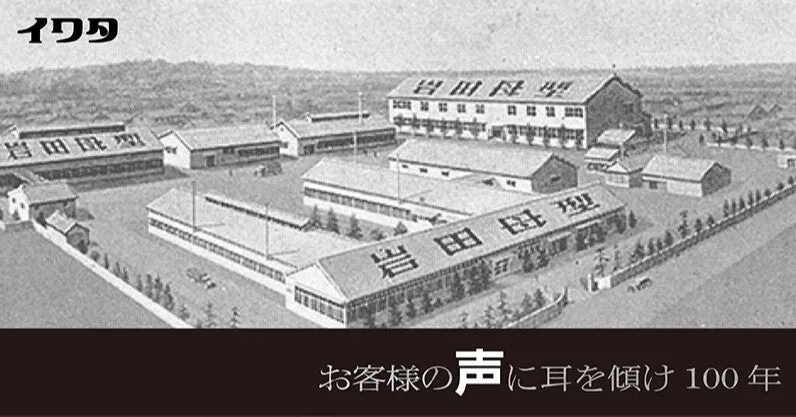
皆さんは、イワタというフォントメーカー、ご存じでしょうか? 1920年(⼤正9年)に岩⽥百蔵⽒が京橋に設⽴した「岩⽥活版⺟型製造所」がイワタのルーツです。ということで、イワタは昨年2020年で100周年を迎えました。おめでとうございます。
イワタの⼯場は、1923年(⼤正12年)の関東⼤震災のあと、⼤森に移転しました。1950年代の当時、⽇本に数台しかなかったベントン彫刻機を導⼊し、鋳造活字の元となる⺟型の⾼精度化と⼤量⽣産を実現し、⽇本最⼤の⺟型製造⼯場に成⻑しました。
1950年代は活版印刷が主流の時代でした。活字地⾦(鉛、錫、アンチモンの合⾦)を鋳型である⺟型に流し込んで鋳造活字を作っていました。活版印刷で使⽤される鋳造活字(鉛活字、⾦属活字と呼ばれることもある)は、⽂字の⼤きさ毎に(初号、1号、2号、3号、4号、5号、6号、7号、8号)、⺟型が必要だったのです。そして、⺟型には⽂字のもとになる字⾯(フェース)が刻まれているのです。
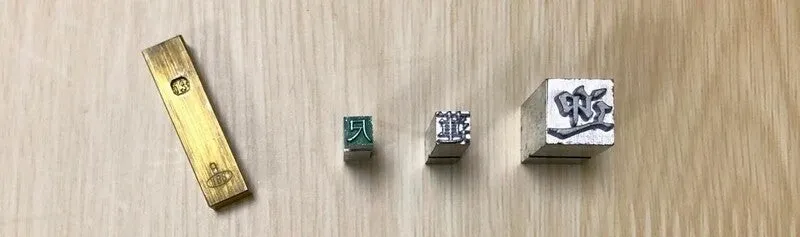
1960年代以降、イワタは全国各地に⽀店や営業所を展開し、1988年に⼭形県天童市にデジタル部⾨である「イワタエンジニアリング」を設⽴します。その後、2001年に岩⽥⺟型製造所とイワタエンジニアリングが経営統合し「株式会社イワタ」が誕⽣します。
イワタはフォント開発だけでなく、顧客要望から制作するカスタマイズフォントの受託も得意としています。⼀般のデザイナーには「イワタLETS」や「イワタ書体ライブラリー」等の商品名のほうに馴染みがあると思いますが、それらに収録されているフォントの多くは、特定のお客様向けに制作した特注フォントだったとのことで、お客様に納品した後、市販化するケースが多いようです。
参考書などで使われているイワタ教科書体、多くの新聞で使⽤されているイワタ新聞書体、リモコンの⽂字等で使⽤されているイワタUDフォントは、元々、お客様からの要望で⽣まれたフォントなのです。お客様からの声に真摯に⽿を傾けてきた姿勢が、バリエーション豊かな現在のイワタ書体シリーズに繋がっていると感じました。
イワタ新聞書体
イワタと⾔えば、新聞書体とUDフォントが代表書体として頭に浮かぶのではないでしょうか。では、新聞書体とUDフォントについて解説していきます。
まずは「新聞書体」をご紹介します。新聞書体といえば、少し平たくつぶれているのが特徴です。通常の書体の字⾯は正⽅のマス⽬に収まった正体の場合が多いと思います。新聞書体は少し扁平かかっている平体です。とはいえ、正体を単に扁平させたわけでなく、平体にしても読みやすい設計がされているとのことです。
新聞書体は、新聞で使⽤される⽬的で開発されましたが、昨今では、ウェブサイトなどのオンスクリーン表現においても⾒出しなどで新聞書体を使⽤するケースが増えてきました。
UDフォント
UDとは「ユニバーサルデザイン」の略称です。「年齢や障害の有無に関係なく、できるだけ多くの⼈が利⽤できるように考えられたデザイン」を意味しています。⽇常⽣活に関わる物の形状や⾊などが主な対象ですが、フォントにおいても、同様の考えに基づき、UDフォントが多くのフォントメーカーからリリースされています。「できるだけ多くの⼈が⾒やすく読みやすくデザインされたフォント」ということです。
先ほど紹介したイワタの新聞書体ですが、1938年(昭和13年)に開発されたイワタの新聞⽤扁平活字は、「できるだけ多くの⼈が⾒やすく読みやすい」の概念で制作されていたようです。
当時、物資統制が強化され、限られた紙⾯にたくさんの⽂字を組まなくてはならず、思案の末、従来の正⽅であった活字を横⽅向に広げ、かつ⽂字のフトコロが広い扁平活字を考案したそうです。70年以上経った今でも、⽇本の新聞⽂字と⾔えばこの扁平⽂字なのです。新聞というメディアにおいて、読みやすさを追求した結果、この書体スタイルが新聞書体ということなのだと感じました。
さて、「UDフォント」という⾔葉はイワタが2006年12⽉に「イワタUDフォント」として発売したものが始まりです。それまでも視認性や可読性を意識してデザインされたフォントはありますが、フォントデザインをUDの観点から研究し開発されたものはありませんでした。
2004年にパナソニック(当時は松下電器産業)とイワタは共同で、リモコン等で使⽤する為のUD視点のフォントを開発しました。ターゲットは横組みかつ10⽂字以下の短⽂であり、電機製品の筐体に印刷される操作表⽰⽤の⽂字の設計でした。
仕様策定と評価はパナソニックが⾏い、⽂字デザインはイワタが担当しました。2006年の春にパナソニックに「PUDフォント(Panasonic Universal Design Font)」として納⼊され、そののち同じものが「イワタUDフォント」として⼀般発売されました。以降UDフォントが広く普及し、フォントメーカー各社から、それぞれのUDフォントが発売され、現在に⾄ります。
イワタでは、UD視点で書体を評価するための4つの要素である「視認性」「判読性」「デザイン性」「可読性」が設定されました。
「視認性」は、⽂字そのものの⾒やすさ、⽂字の⾻格、フトコロの取り具合、⼤きさ、画線の太さなどが影響します。「判読性」は、誤読しにくさ、他の⽂字との判別のしやすさになります。近接ラインを離したり、紛らわしい⽂字は差別化を⾏ったりします。「デザイン性」は、⽂字のシンプルさや美しさ、整理・整合性であり、時には製品にふさわしいかどうか、購買意欲を失わないかということも問われます。「可読性」は、単語や⽂章にしたときの読みやすさです。漢字と仮名の⼤きさのバランスや字間と⾏間の適切なバランスが必要とされます。
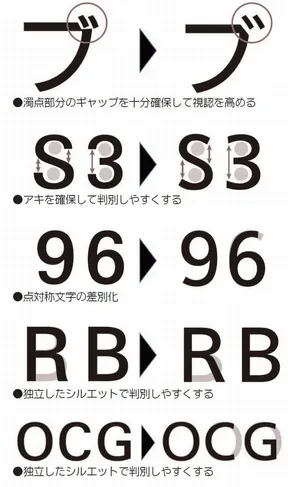
イワタUDフォントは、ゴシックに限らず、さまざまなシーンで使いやすいように、いくつかの書体でUDフォントとして追加リリースされました。
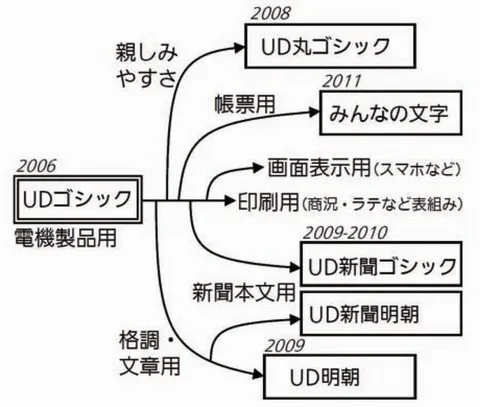
ところで、「UDという名前が付いている書体なら、どんな環境でも読みやすい書体」と勘違いされているケースは少なくないように感じます。短いテキスト表現に向いているUDフォントを本⽂に使⽤すれば、読みづらい印象になる可能性が⾼いです。
紙のメディアで使⽤されることを前提にしているのか、ディスプレイで使⽤されることを前提にされているのか、使われる解像度がどのくらいなのか等々の要因や、実際にフォントが使⽤されるコンテクスト(前後関係、背景等)に応じて、⾒やすくて読みやすい書体は変わってきます。
⽇本に限らず、全世界でたくさんのフォントがリリースされてきました。多くの書体が「できるだけ多くの⼈が⾒やすく読みやすくデザインされたフォント」を意識して丁寧に制作されたフォントが多いです。使われる環境に応じて、実際にテキストを組んでみて⽐べてみたり、周りからの意⾒を聞いたりして、書体選定することが⼤事なことだと思います。
イワタでは、新聞書体やUDフォント以外にどんなフォントがあるの?
イワタからリリースされているフォントは、新聞書体やUDフォント以外にも素敵なフォントがたくさんあります。筆者が選んだおすすめ書体をいくつかご紹介します。
イワタの新書体、東亜重⼯製フォント「東亜重⼯」
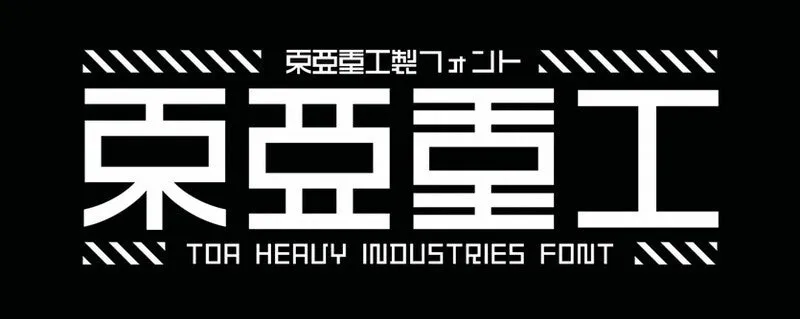
真⾯⽬で堅い書体が多い印象のあるイワタのフォントですが、昨年には漫画家の弐瓶勉⽒の様々な作品に登場する特徴的な⽂字を同⽒原案・監修のもと新たに開発した東亜重⼯製フォント「東亜重⼯」が発売されました。
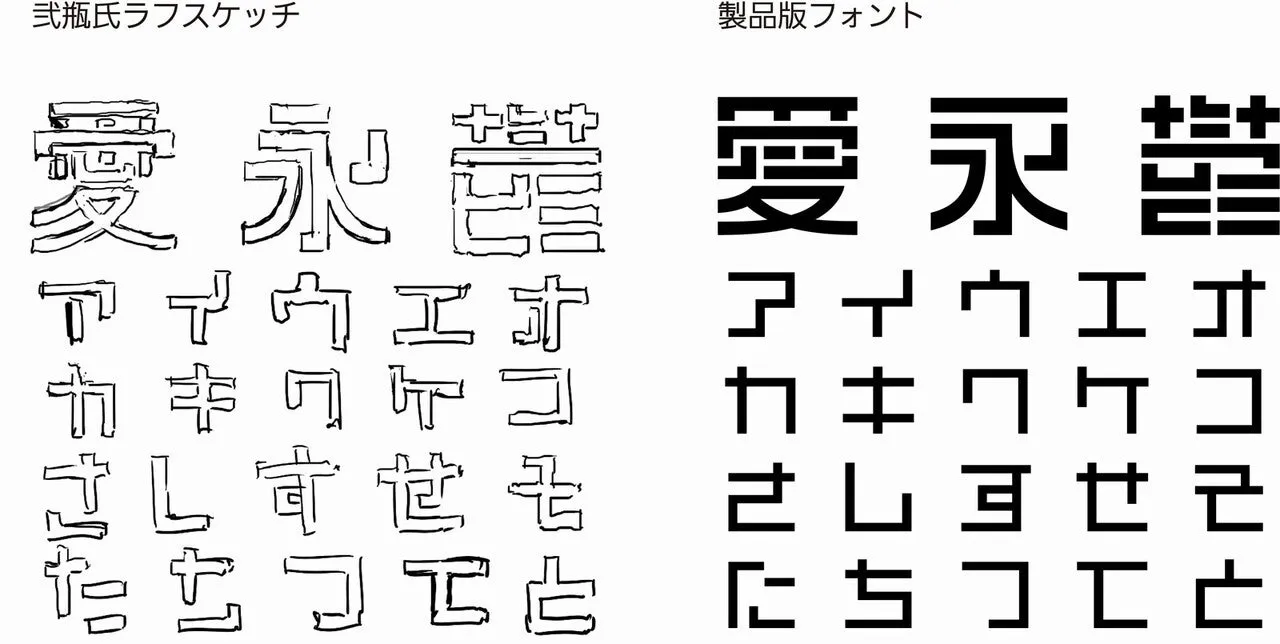
直線を基本とし、必要最低限の無機質なカーブ、パーツの簡略化など弐瓶⽒の世界観を形にしたこの書体は読めそうで読めない、読めなさそうで読める。UDフォントとは真逆を⾏くフォントです。
発売時には、「東亜重⼯」に汚れ加⼯を施した「東亜重⼯ GRUNGE」やフィギュア「1/12 合成⼈間 初号試験型イ」がついた限定版が発売されるなど、その界隈では少し話題になったそうです。